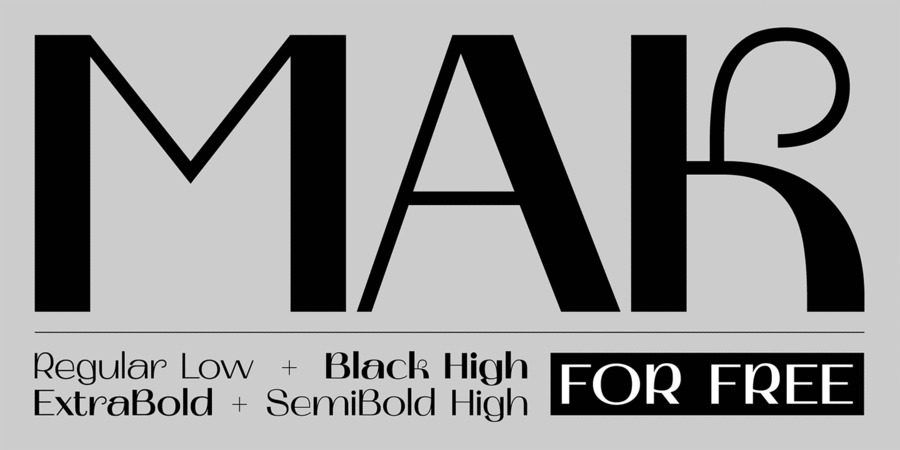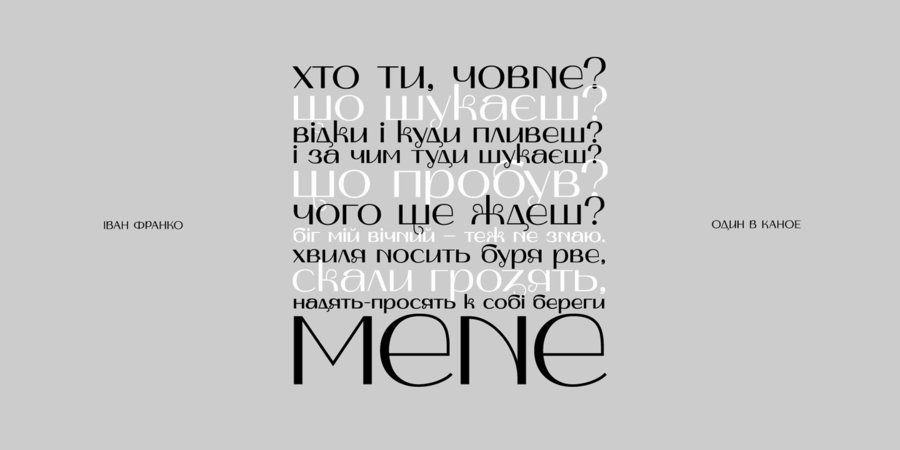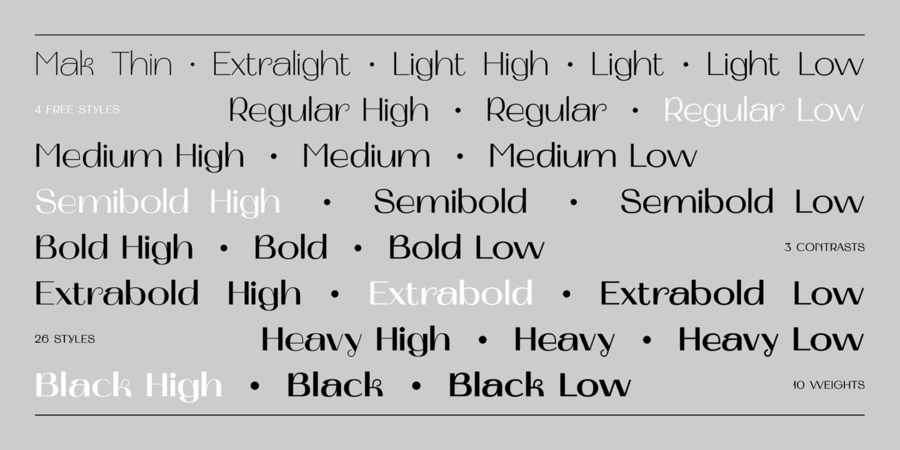
Mak – акцидентний шрифт з українським характером, натхненний сучасною українською музикою.
Це велике оновлення перших двох безкоштовних накреслень Mak (SemiBold High і Black High), які були створені у 2019 році та набули широкого поширення серед безкоштовних декоративних шрифтів. Велике оновлення полягало не лише в додаванні більшої кількості накреслень, але й у вдосконаленні окремих літер і додаванні нових. Тепер Mak підтримує всі мови на основі латиниці та європейську кирилицю.
Експеременти з історичними формами, контрастність, сміливі конструкції створюють новий образ української кирилиці та латиниці на основі неї.
Шрифт розробив Валентин Ткаченко у 2019-2022 році.
Асоціації з сімейством шрифтів MakОсобистість і характер гарнітури:
делікатний, інтимний, тонкий, легкий, ритмічний, неформальний, грайливий, цікавий, оригінальний, характерний, привітний, живий, прикольний, самобутній, легковажний, динамічний, молодіжний, потішний, експериментальний, естетський, богемний, манірний, гнучкий, модний, вишуканий, якісний, весняний, прозорий, повітряний, вигнутий, артистичний, музичний, радісний, неординарний, дивний, творчий, симпатичний, ламповий, красивий, сексуальний, міський, свіжий, гладенький, незвичайний, позитивний, популярний, гарненький, нічний, ювелірний, доброзичливий, добродушний, вигадливий, смішний, мажорний, хитрий, усміхнений, щасливий, вінтажний, нонконформістський, мінливий, оманливий, ефектний, дзвінкий, задерикуватий, екзотичний, дотепний, виразний, театральний, претензійний, епатажний, гострий, яскравий, літній, помітний, демонстративний, екстравагантний, неоновий, невагомий, ніжний, дротяний